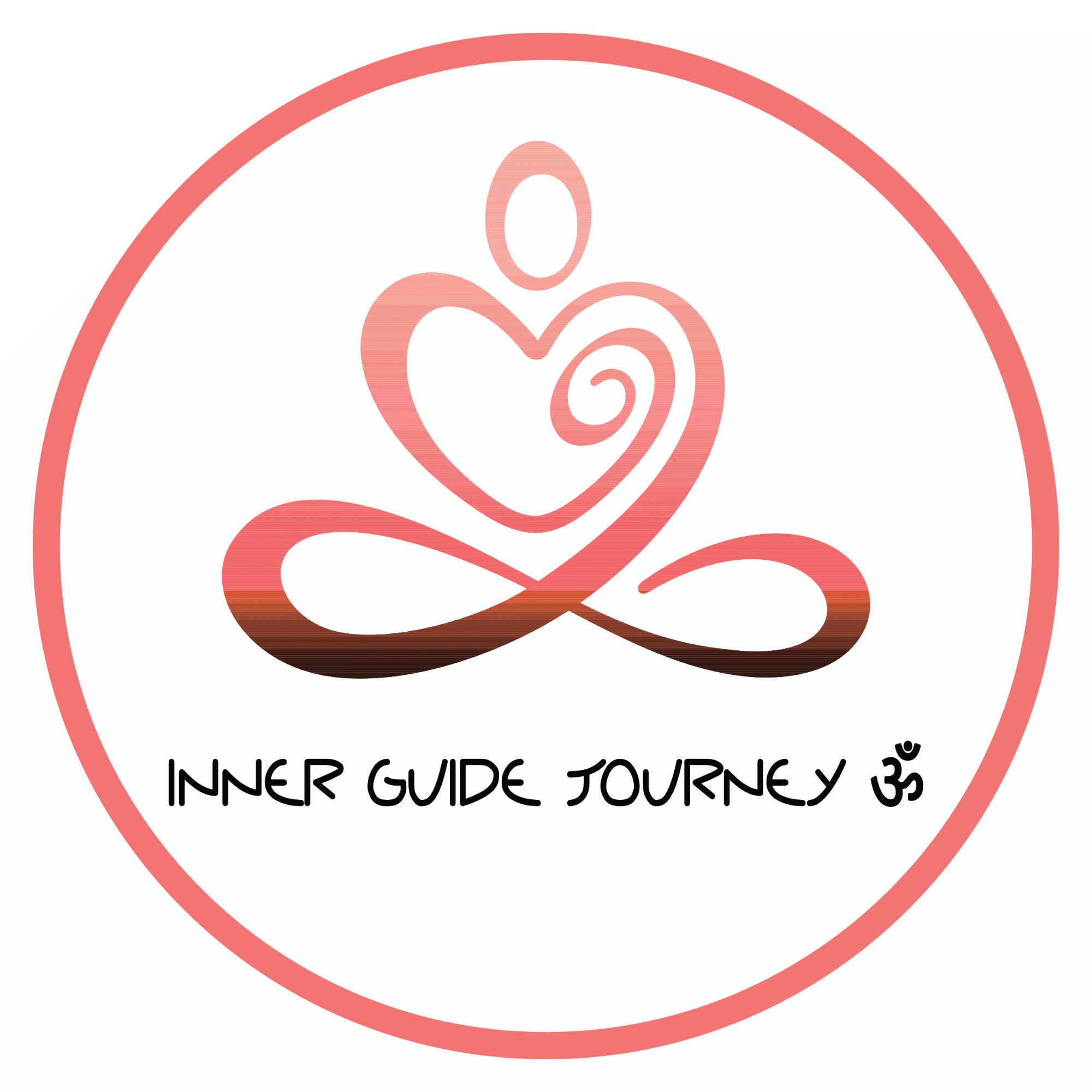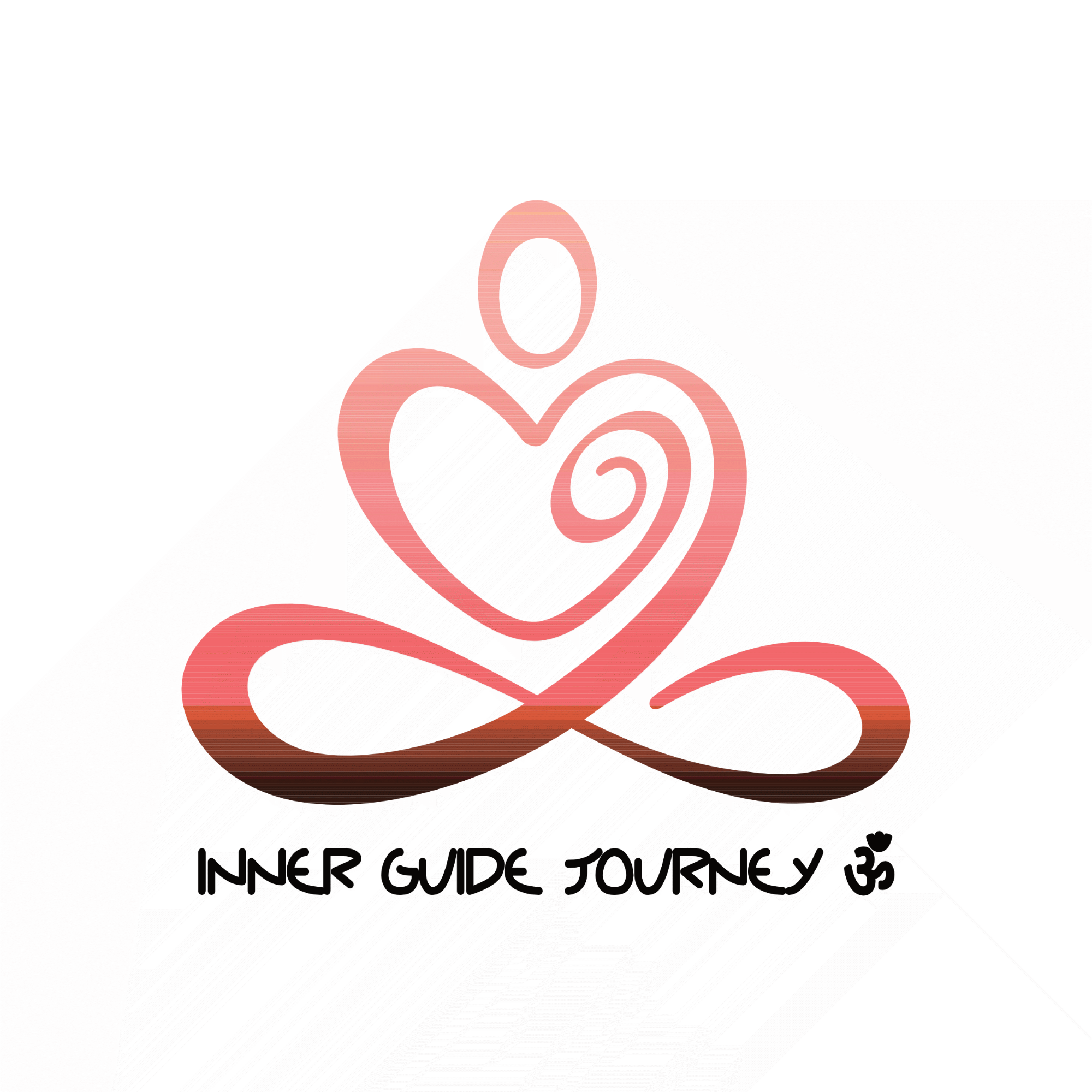
Welche Schrift passt für diesen Schriftzug & Symbol?
Im Anhang seht Ihr mein Logosymbol mit dem Schriftzug "Inner Guide Journey". Die bisherige Schrift ist "Tibet", jedoch ist diese in kleinen Profilbildern, wie z. B. Instagram sehr schlecht lesbar. Daher möchte ich mich von dieser Schrift verabschieden.
Was würdet Ihr meinen, welche freie (oder ggfs. kostenpflichtige) Schrift passt, besser lesbar ist und im Gesamtbild harmonisch auch zum Thema passt?
Ich würde eine kontrastreiche Schrift zum Logo nehmen, die auch tibetisch kann.
Die beiden obigen sagen mir nicht so zu, wenn sie für sich alleine im Lateinischen stehen.
Für kostenfrei ist die Noto ein gute Wahl, denke ich.
Leider lässt sich diese Schrift hier nicht mit eigenem Text vorher ausprobieren. Da werden statt meinem Text in dieser Schrift hochkantige Rechtecke angezeigt. Hätte mich interessiert, um zu schauen, ob mir diese gefällt. Bei der  Tibet Museum Schrift war der erste Impuls positiv, jedoch verflüchtigte sich dieser recht schnell wieder.
Beziehst Du ihn auf Deine eigene Schriftvorschläge?
Ja, auf die Designpiraten-Schriften. Die mögen im gemischsprachigen Umfeld rocken, aber für sich alleine in einem lateinischen Umfeld find ich die quirkig.
Mir kam da spontan eine Pinsel- oder Handschrift in den Sinn … was Persönliches, Eigenes, Inneres, Individuelles, gern auch deine eigene Handschrift, damit es nicht austauschbar ist.
Nur schnell hingeschmissen:
Bin ich ganz bei Dir. Für sich alleine stehend, nerven diese Schriften vermutlich recht schnell. Somit sind beide  raus, da ich eine Schrift passend zum Thema & Logosymbol suche, die ich auf meiner Webseite & bei meinem Insta Kachel Content als H1 nutzen wollte. Im Moment ist es noch immer die Tibet. ;-)
Ich hatte den Link der Schrift eingefügt, die nicht zum Testen funktionierte ... die PEMA Tibetan ... Wie sieht diese denn mit INNER GUIDE JOURNEY aus?
Ich könnte mal probieren, den Schriftzug mit meiner Handschrift zu schreiben. :-)
Bei Deinem Vorschlag muss ich länger hinschauen ... Gut finde ich die Idee, das OM Zeichen nach unten zu setzen, wobei ich unter dem Schriftzug noch by Doro Miko (bzw. meinen echten Namen) stehen hatte.
Würde aber vielleicht trotzdem noch passen. Nur, ob diese Schrift auch als H1 für meine Webseite geeignet ist ... hhhhmmm, das müsste ich probieren. Das ergebe ein komplett anderes Design. Oder ich löse mich von Schriftzug = H1. Wie heißt denn die obige Schrift?
Das ॐ würde ich aber im selben Duktus schreiben, in meinem Beispiel ist das nur angedeutet. Wenn du alles von Hand schreibst, würde es auch zusammenpassen.
Die Pinsel-Idee finde ich gut! muss aber gut gemacht sein und auf jeden Fall individuell und kein Font (fürs Logo)!
Hier würde ich den pragmatischen Weg gehen und einfach zwei Varianten erstellen: Logo mit Schriftzug für große Größen, nur das Signet für Profilbilder. Wenn’s gut gemacht ist sollte es aussagekräftig genug sein.
Oder ich löse mich von Schriftzug = H1.
Ja! Ich finde Logo-Schrift und Überschriften dürfen uns sollten manchmal unterschiedlich sein.